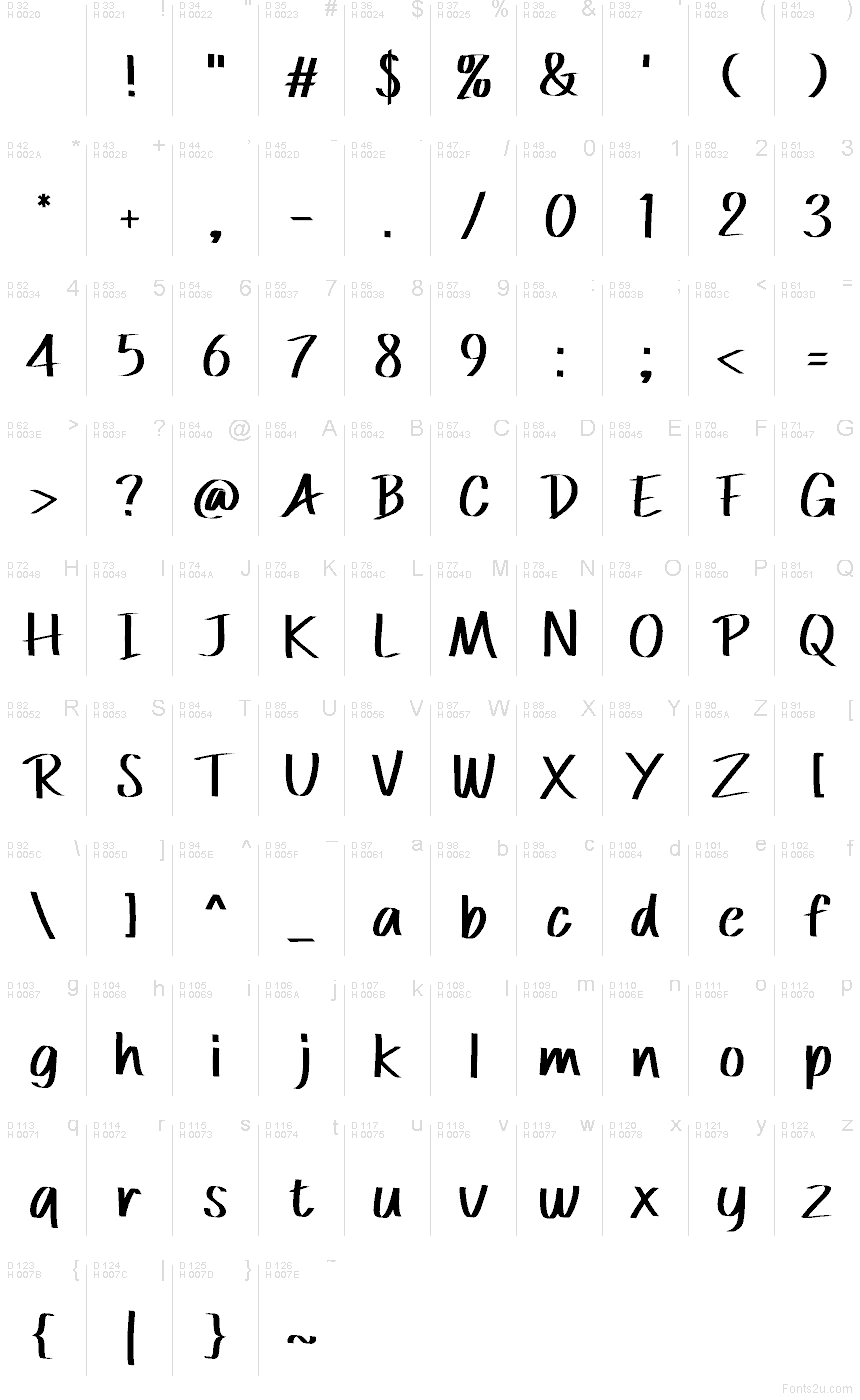
Going Alone
Going Alone, créée par Hello Good Studio, est une police manuscrite gratuite au rythme calligraphique incliné. Ses longs traits fuselés confèrent aux lettres une allure vive, comme tracée à la plume. Le dessin est étroit et fluide, avec des liaisons courbes et un balayage subtilement dynamique qui maintient le mouvement d'un caractère à l'autre.
Going Alone est idéale pour les logos signatures, les cartes d'invitation, le packaging, les citations sur les réseaux sociaux et les titres courts, car sa fluidité apporte une touche personnelle sans jamais manquer de lisibilité. Cette police gratuite est également parfaite pour les affiches et les éléments de branding nécessitant une touche manuscrite à la fois raffinée et directe.